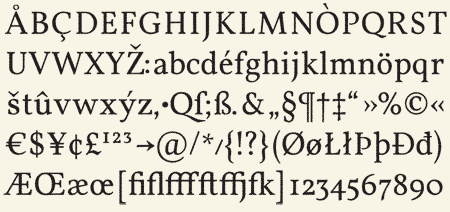
Antiqua mit Mediävalziffern?
Ich beschäftige mich hobbymäßig mit Typographie und suche momentan nach einer neuen Schrift, in der ich meine Arbeiten layouten kann (die Abschlußarbeit steht bevor).
Bisher habe ich immer Georgia verwendet, weil ich ein Faible für Mediävalziffern habe; jetzt würde ich gerne mal eine neue Antiqua ausprobieren, habe aber keine Lust, Geld dafür auszugeben. Kann mir jemand sagen, wo ich also eine Antiqua OSF herbekomme, und zwar für lau?
Sonst muß ich doch bei Georgia bleiben...
Die Schrift soll wahrscheinlich auch noch Käpitälchen besitzen, in 5
Gewichtungen von Light bis Black vorhanden sein und noch ne Sans-
Variante haben, wa. :lol:
Entschuldige meinen Sarkasmus, aber für "lau" gibbet nich wirklich viele
Schriften, mit denen man arbeiten kann.
Falls du die Adobe Creative Suite hast, kannst du mit der Antiqua namens Minion Pro arbeiten, die wird dort mitgeliefert (besitzt auch Mediävalziffern und Kapitälchen und vieles mehr...)
Vielleicht kommt die hier in Frage? es gibt nur einen Schnitt, der aber sehr solide ausgeführt ist. Allerdings gibt es sie nur im OpenType Format.
Vollkorn-Brotschrift von Friedrich Althausen: